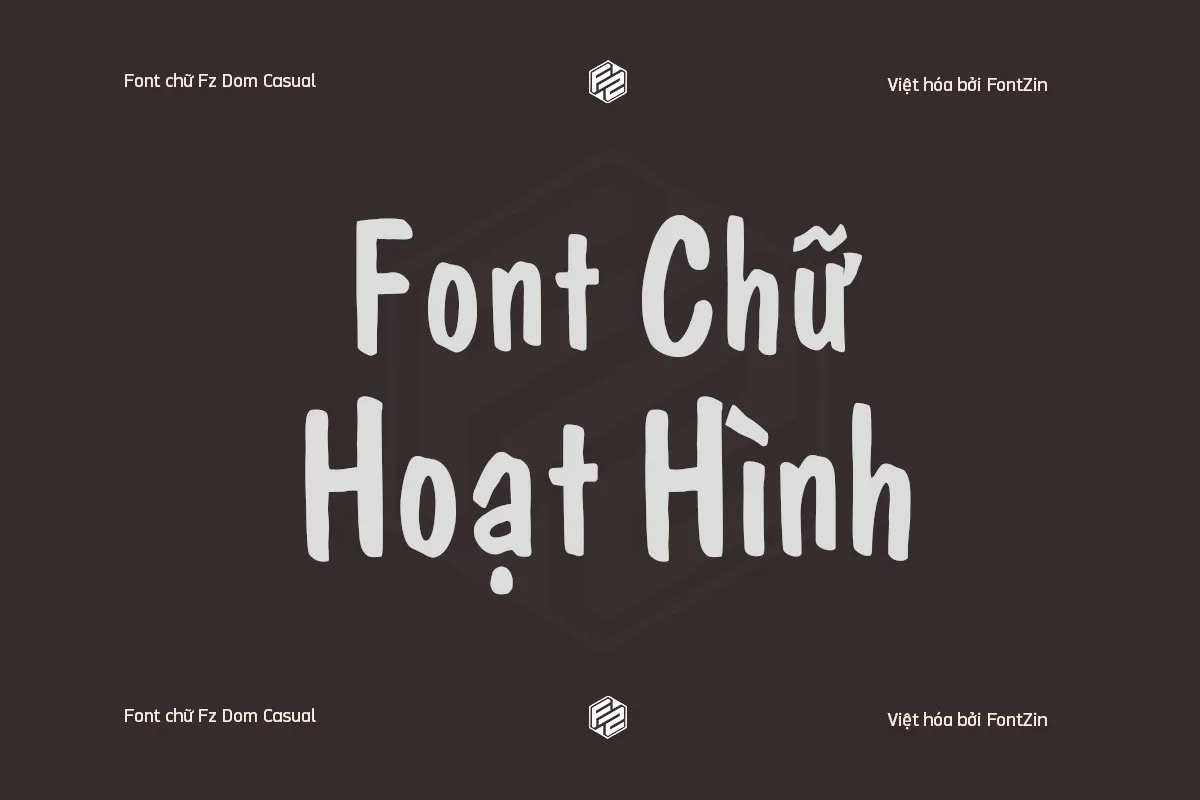
Font hoạt hình Việt hóa Fz Dom Casual
Fz Dom Casual là kiểu chữ nổi bật với phong cách bút lông tự nhiên, mang đến cảm giác thoải mái, gần gũi nhưng không kém phần tinh tế. Với sự chăm chút từ  Font Miễn Phí Fz Dom Casual đã được tối ưu hóa để hỗ trợ ngôn ngữ tiếng Việt, mở rộng khả năng ứng dụng cho các nhà thiết kế và sáng tạo nội dung.
Phiên bản Việt hóa Fz Dom Casual, được thực hiện bởi   Font Miễn Phí, mang đến trải nghiệm hoàn toàn mới cho người dùng Việt Nam mà vẫn giữ nguyên nét tinh tế và đặc trưng vốn có của kiểu chữ gốc. Một số ưu điểm nổi bật:
• Hỗ trợ đầy đủ tiếng Việt: Với đầy đủ dấu và ký tự đặc biệt, Fz Dom Casual đảm bảo khả năng hiển thị tốt nhất cho các nội dung tiếng Việt.
• Thiết kế đậm chất hoài cổ: Phù hợp cho các dự án mang phong cách retro, vintage, hoặc những thiết kế hướng tới sự gần gũi và tự nhiên.
• Tính ứng dụng cao: Có thể sử dụng cho tiêu đề, poster, bao bì sản phẩm, bảng hiệu hoặc nội dung sáng tạo khác.
• Fz Dom Casual ứng dụng đa dạng trong thiết kế
Font hoạt hình Việt hóa Fz Dom Casual
Fz Dom Casual không chỉ là một font chữ mà còn là công cụ sáng tạo mạnh mẽ, mở rộng khả năng ứng dụng trong nhiều lĩnh vực:
1. Truyền thông thị giác
• Poster và banner: Với phong cách hoạt hình và nét chữ tự nhiên, Fz Dom Casual là lựa chọn tuyệt vời để tạo sự nổi bật cho các thiết kế quảng cáo.
• Video tiêu đề và credit: Lý tưởng cho các video truyền cảm hứng, giáo dục, hoặc nội dung giải trí mang màu sắc hoài niệm.
2. Xây dựng thương hiệu
• Logo: Tạo điểm nhấn độc đáo cho thương hiệu trong các lĩnh vực như đồ uống, cửa hàng sáng tạo, hoặc sản phẩm handmade.
• Bảng hiệu và bao bì: Fz Dom Casual mang lại vẻ thân thiện và dễ nhận biết, giúp thu hút khách hàng một cách tự nhiên.
3. Nội dung giáo dục và trẻ em
• Với phong cách hoạt hình tươi vui, font chữ này đặc biệt phù hợp cho các ấn phẩm giáo dục, sách thiếu nhi, hoặc sản phẩm trò chơi tương tác.
4. Truyền tải cảm xúc trong in ấn
• Dành cho thiệp mời, thư cá nhân, hoặc các thiết kế mang tính cá nhân hóa. Fz Dom Casual giúp truyền tải thông điệp với sự ấm áp và tinh tế.
Hình ảnh Demo Font chữ hoạt hình Việt hóa Fz Dom Casual